「あつまれ どうぶつの森(あつ森)」の雰囲気にぴったりな日本語フォント
あつまれ どうぶつの森(あつ森)のような世界観を作るなら、文字にも「やさしさ」「丸み」「暮らしの温度感」があると、デザイン全体がぐっと近づきます。
島の掲示板、住民との会話、案内所のメニュー、手作りイベントの告知など、少し丸くて親しみやすいフォントは、ほのぼのしたゲーム風デザインと相性抜群です。
今回は、公式フォントの完全再現ではなく、「あつ森っぽい雰囲気」を作りやすい日本語フリーフォントをピックアップしました。丸ゴシック、手書き風、レトロな看板風、子どもっぽいポップ体など、ナチュラルでかわいい島暮らしの空気に合わせやすいフォントを中心に紹介します。
あつ森風のほのぼのデザインに使いやすい日本語フリーフォント
以下のサンプルのように、あつ森風のほのぼのデザインの雰囲気にぴったりなフォントをご紹介します。
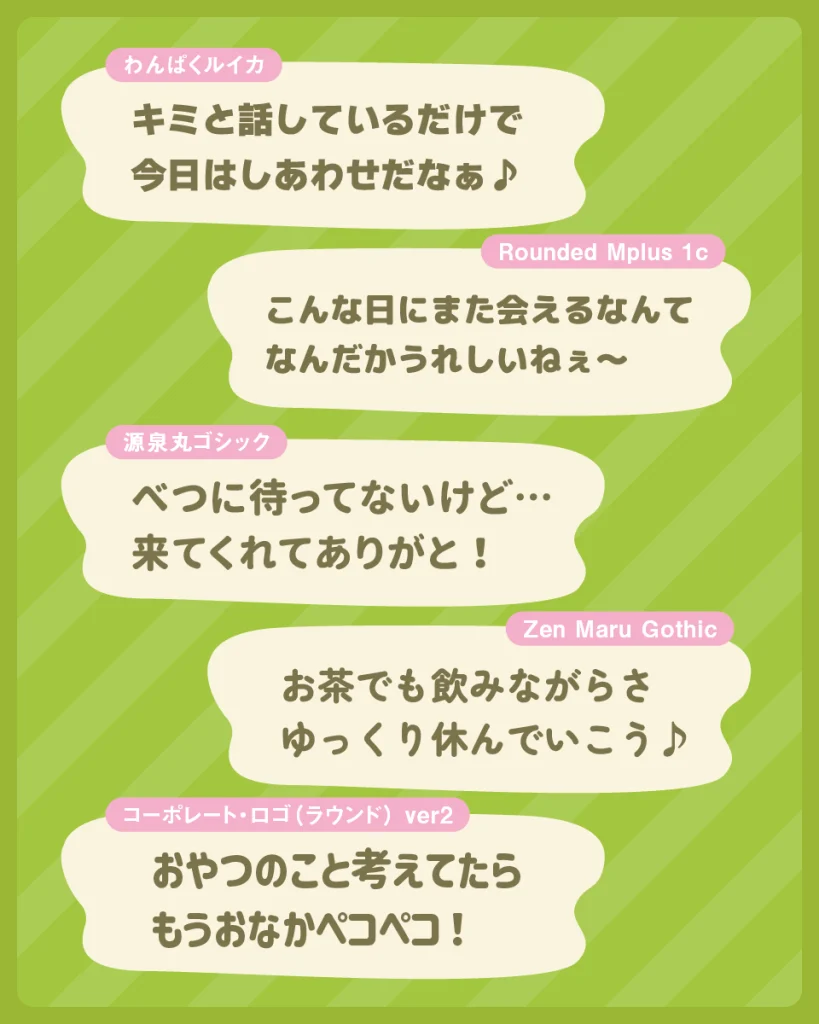
きよすなゴシック
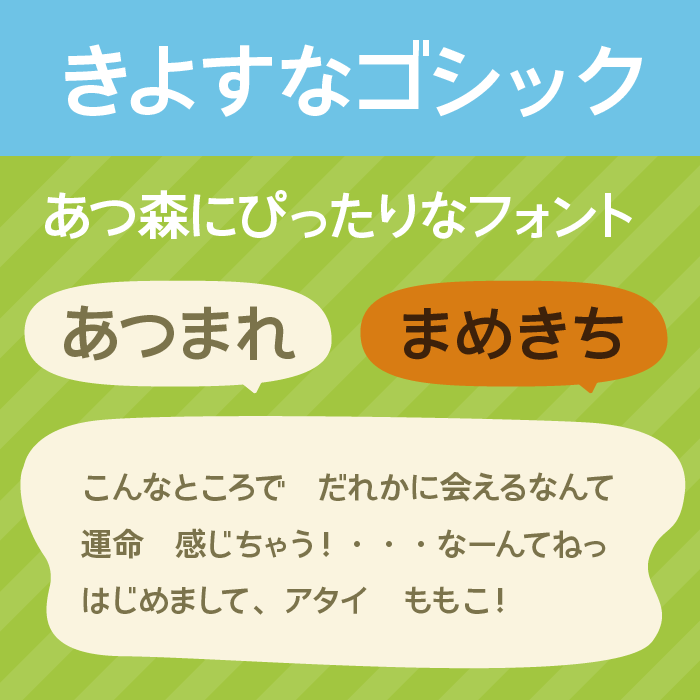
| 使用用途 | 会話UI/見出し/案内文/島の掲示物 |
| おすすめの世界観 | あつ森風/島暮らし/やさしいゴシック/住民会話/ナチュラル |
きよすなゴシックは、すっきりしたゴシック体に、ほんのり丸く親しみやすい表情を加えた日本語フォントです。
クセが強すぎないため、あつ森風の会話ウィンドウや案内文のように、長めの文章をやさしく読ませたい場面に向いています。かっちりしすぎないのに整って見えるので、島の掲示板、イベント告知、住民プロフィール、ナチュラルなゲーム風UIにも使いやすい一本です。
永代ゴシック
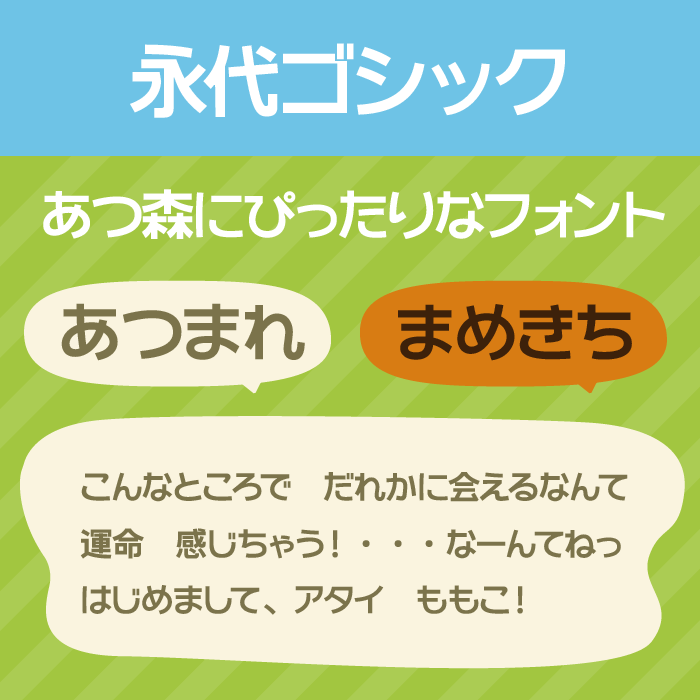
| 使用用途 | タイトル/見出し/会話UI/イベント告知 |
| おすすめの世界観 | あつ森風/まち案内/やわらかい見出し/ほのぼのゲーム/島内イベント |
永代ゴシックは、丸みと安定感のバランスがよく、見出しにも本文にも使いやすいゴシック体です。
太さに安心感がありながら、角がきつく見えにくいので、あつ森のようなほのぼのした世界観にも自然になじみます。島の名前、イベントのお知らせ、住民との会話テキストなど、少し目立たせたいけれど強くなりすぎたくない場面にぴったり。清潔感のあるゲーム風デザインに向いたフォントです。
新レトロ丸ゴシック
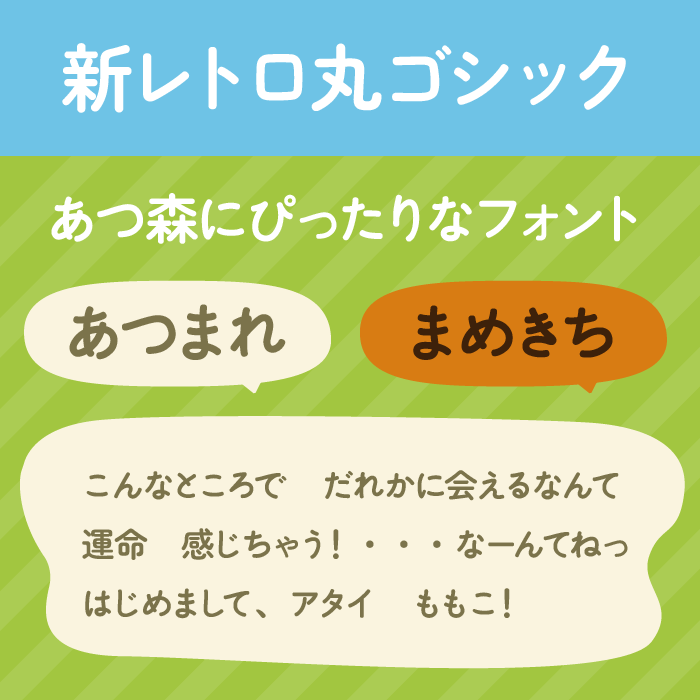
| 使用用途 | 見出し/会話文/看板/レトロな案内 |
| おすすめの世界観 | あつ森風/レトロ商店街/島の看板/喫茶店/やさしい懐かしさ |
新レトロ丸ゴシックは、昔の看板や印刷物を思わせる懐かしさと、丸ゴシックらしいやわらかさをあわせ持つフォントです。
あつ森風のデザインでは、島の商店、喫茶店、手作り看板のような、少しレトロで落ち着いた雰囲気によく合います。文字に温度があるので、ただ可愛いだけでなく、暮らしの中にある案内板のような親しみも出せます。会話UIにも見出しにも使いやすい万能タイプです。
えるまー
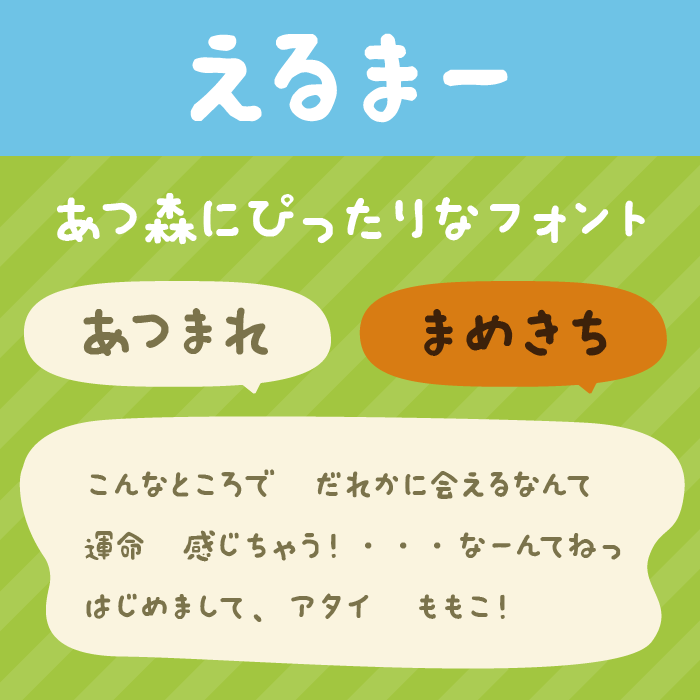
| 使用用途 | 手書きメモ/掲示板/会話文/クラフト風デザイン |
| おすすめの世界観 | あつ森風/手作り感/住民メモ/クラフト/素朴でかわいい |
えるまーは、クレヨンやマーカーで書いたような、素朴で丸い手書き感が魅力のフォントです。
きれいに整えすぎない字形が、あつ森の手作り家具や島の掲示板のような空気とよく合います。住民から届いたメモ、イベントのお知らせ、DIYレシピ風の見出しなど、少し人の手を感じさせたいデザインにぴったり。やさしく、のんびりした世界観を作りたいときに使いやすいフォントです。
こども丸ゴシック
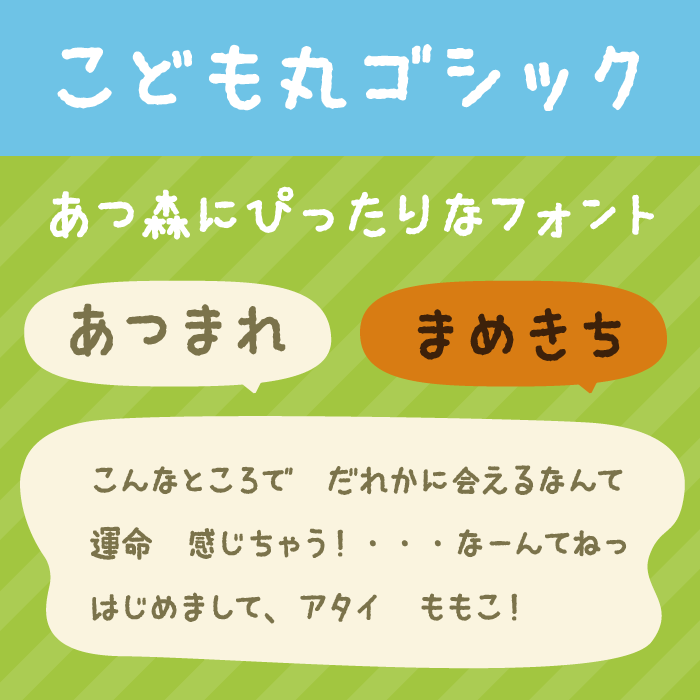
| 使用用途 | 手書き風見出し/会話UI/お知らせ/子ども向けデザイン |
| おすすめの世界観 | あつ森風/ゆるい島暮らし/子どもっぽさ/手作り掲示物/かわいい案内 |
こども丸ゴシックは、子どもが丁寧に書いたような、やわらかく素直な表情を持つ丸ゴシック体です。
字形に少し揺れがあり、手書き感が出るため、あつ森風の島内掲示板や、住民の一言メッセージにとてもよく合います。可愛さはありますが甘くなりすぎず、ナチュラルな雰囲気にまとまるのも魅力。ほのぼのしたイベント告知や、親しみやすい会話文に使いたいフォントです。
コーポレート・ロゴ(ラウンド)
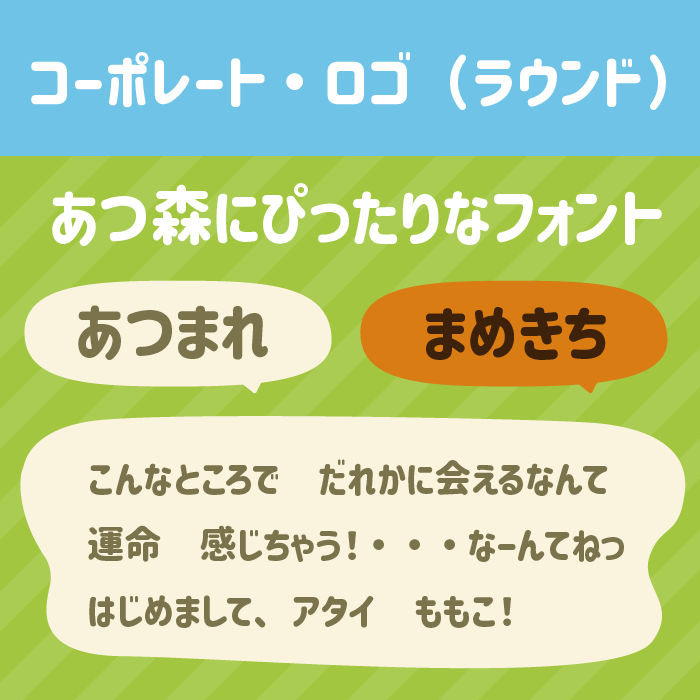
| 使用用途 | タイトルロゴ/見出し/メニュー/案内パネル |
| おすすめの世界観 | あつ森風/読みやすいUI/島の施設案内/ポップな丸ゴシック/清潔感 |
コーポレート・ロゴ(ラウンド)は、太めで読みやすいロゴ向けの丸ゴシック体です。
文字の骨格がしっかりしているため、あつ森風のデザインでは、島の施設名、メニュー画面、イベントタイトルなど、ぱっと読ませたい場所に向いています。丸みがあるので事務的になりすぎず、ゲームUIらしいやさしさも残せるのが良いところ。可愛さと視認性を両立したいときに頼れるフォントです。
はこべら丸ゴシックA
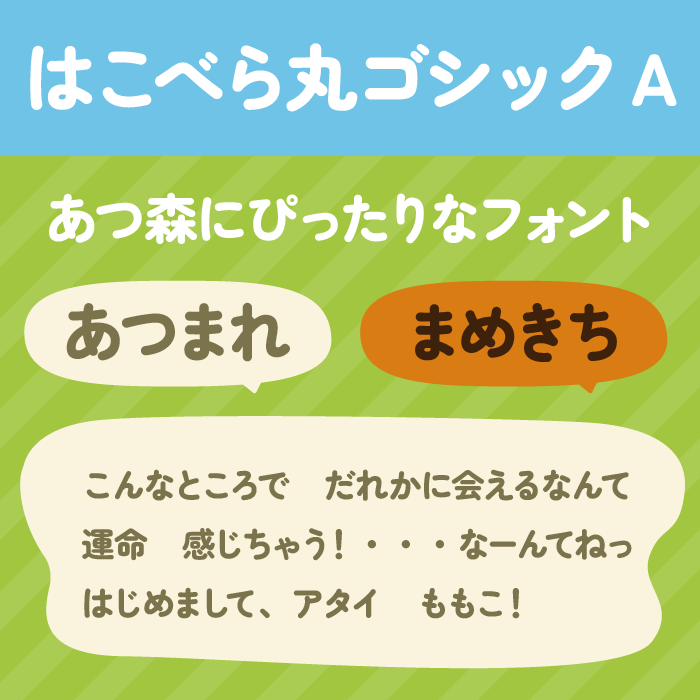
| 使用用途 | 本文/会話UI/見出し/情報パネル |
| おすすめの世界観 | あつ森風/会話ウィンドウ/ナチュラルUI/やさしい丸ゴシック/島暮らし |
はこべら丸ゴシックAは、丸ゴシックの親しみやすさと、本文にも使える落ち着いた読みやすさを持つフォントです。
太さの展開もあり、見出しから会話文まで統一感を出しやすいのが魅力。あつ森風のデザインでは、吹き出しの中のセリフ、住民紹介、島の案内パネルなどに向いています。角がやわらかく、画面全体をやさしい印象にできるため、ほのぼのしたゲーム風UIに合わせやすい一本です。
ZEN丸ゴシック
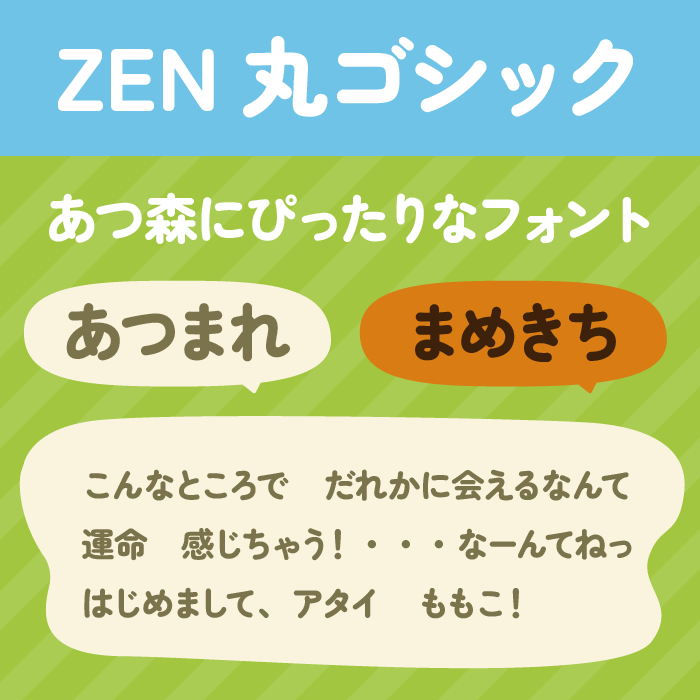
| 使用用途 | 本文/会話UI/見出し/Webデザイン |
| おすすめの世界観 | あつ森風/ナチュラル/読みやすい会話文/暮らし系デザイン/やさしいUI |
ZEN丸ゴシックは、やわらかな丸みと高い可読性を兼ね備えた、使いやすいフォントです。
クセが控えめなので、あつ森風の会話文や説明文のように、読む量が多い場所にも自然に使えます。太めのウェイトを選べば見出しにもなり、軽めのウェイトなら穏やかな本文にもぴったり。島暮らし、カフェ、手作り雑貨、自然系のWebデザインなど、やさしく整った雰囲気を作りたいときにおすすめです。
源泉丸ゴシック
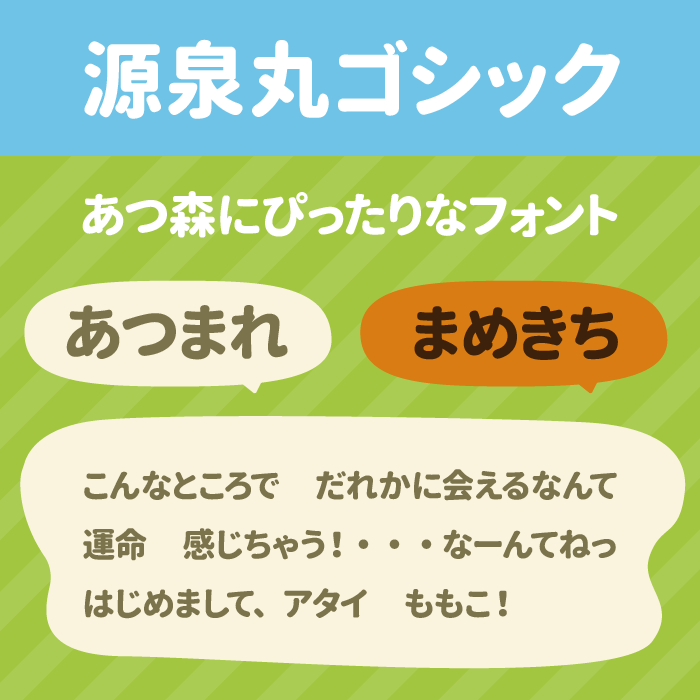
| 使用用途 | 本文/会話UI/見出し/ゲーム画面 |
| おすすめの世界観 | あつ森風/やさしいゴシック/島内アナウンス/情報表示/ナチュラル |
源泉丸ゴシックは、読みやすいゴシック体をベースに、角を丸くしたやさしい印象のフォントです。
ウェイトが豊富なので、見出しは太く、本文は軽くといった使い分けがしやすく、あつ森風のUI全体をひとつの雰囲気でまとめられます。丸みがありながら文字の形は素直なので、会話文、説明テキスト、メニュー、島内アナウンスなど幅広く活躍。落ち着いた可愛さを出したいときに便利です。
ポプらむ☆キウイ
| 収録文字 | ひらがな/カタカナ/英字/数字/記号/漢字 |
| 使用用途 | タイトル/見出し/イベント告知/ポップなバナー |
| おすすめの世界観 | あつ森風/元気な島イベント/かわいい見出し/ポップ/フェス感 |
ポプらむ☆キウイは、太く丸い文字に、ぷっくりした可愛さを詰め込んだポップ系フォントです。
あつ森風の中でも、島内イベントや季節のお祭り、住民参加型の告知など、明るくにぎやかな場面によく合います。本文よりも短い見出しで使うと存在感が出やすく、「釣り大会」「花火の日」などのタイトルにもぴったり。ほのぼのした世界に、少し元気なアクセントを加えたいときにおすすめです。
源柔ゴシック
| 収録文字 | ひらがな/カタカナ/英字/数字/記号/漢字 |
| 使用用途 | 本文/会話UI/見出し/案内文 |
| おすすめの世界観 | あつ森風/やさしいUI/住民会話/島の案内/落ち着いた丸み |
源柔ゴシックは、源ノ角ゴシック系の読みやすさを残しながら、角をやわらかく丸めた日本語フォントです。
しっかり読めるのに硬くなりすぎないため、あつ森風の会話UIや案内文にとても使いやすいフォントです。太さや丸みの印象を調整しやすく、画面全体を穏やかにまとめられるのも魅力。住民との会話、島内ニュース、プロフィール欄など、読みやすさを大事にしたい場面に向いています。
Rounded M+
| 収録文字 | ひらがな/カタカナ/英字/数字/記号/漢字 |
| 使用用途 | 本文/会話UI/メニュー/見出し |
| おすすめの世界観 | あつ森風/シンプルUI/ナチュラルゲーム/丸ゴシック/日常感 |
Rounded M+は、M+系フォントを丸くした、シンプルで使いやすい丸ゴシック体です。
余計な装飾が少ないため、あつ森風の世界観に合わせても主張しすぎず、会話文やメニュー表示をすっきり見せられます。丸みの種類や太さを選びやすいので、見出しは少し太め、本文は読みやすく控えめ、といった使い分けにも便利。穏やかで清潔感のあるゲーム風デザインに向いたフォントです。
しんばしごちっく
| 収録文字 | ひらがな/カタカナ/英字/数字/記号/漢字 |
| 使用用途 | 見出し/看板/レトロな案内/タイトル |
| おすすめの世界観 | あつ森風/島の駅前/レトロ看板/商店街/公共施設 |
しんばしごちっくは、昔の駅名標や街の看板を思わせる、レトロであたたかい雰囲気のゴシック体です。
あつ森風のデザインでは、島の案内所、商店、喫茶店、駅前風の看板など、少し懐かしい公共サインのような表現に向いています。丸みと角ばりのバランスがよく、可愛いだけではない生活感を足せるのが魅力。島に昔からある施設名のような、落ち着いた見出しに使いたいフォントです。
わんぱくルイカ
| 使用用途 | タイトル/イベント告知/見出し/子ども向けバナー |
| おすすめの世界観 | あつ森風/元気な島イベント/子どもっぽい可愛さ/遊び心/にぎやか |
わんぱくルイカは、太く元気な字形が印象的な、子ども向けデザインにも使いやすいフォントです。
丸みがありながら勢いもあるため、あつ森風の島イベントや、遊び心のあるタイトルにぴったり。住民たちが集まるお祭り、虫とり大会、手作り告知ポスターのような場面に使うと、楽しい雰囲気が出せます。無料お試し版は収録文字に制限があるため、公開物では使用範囲を確認して使うのがおすすめです。